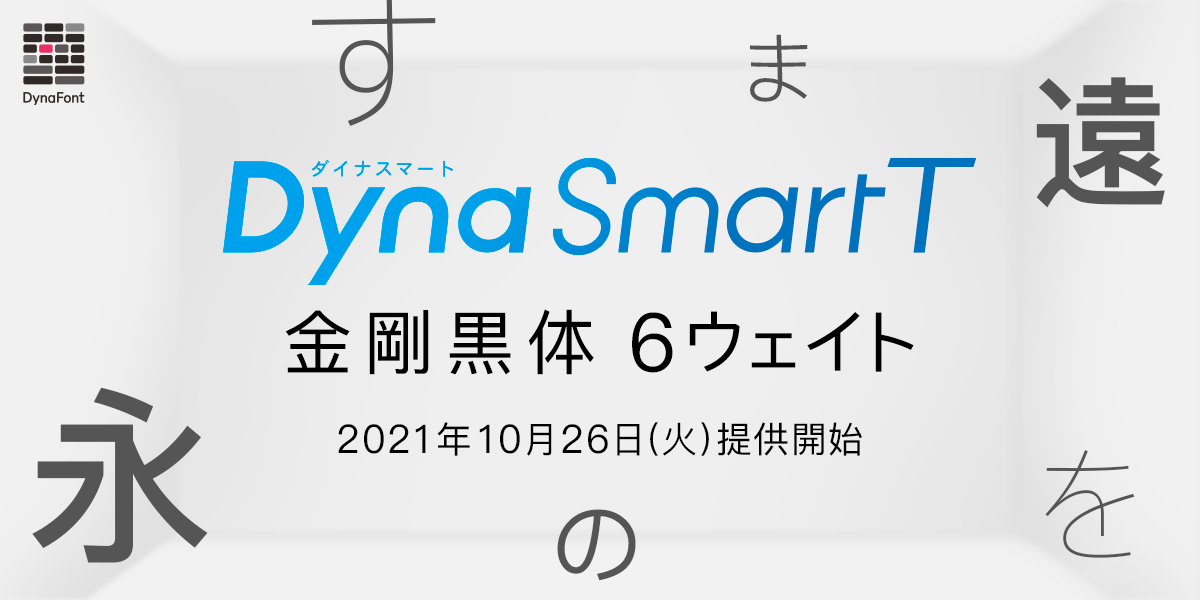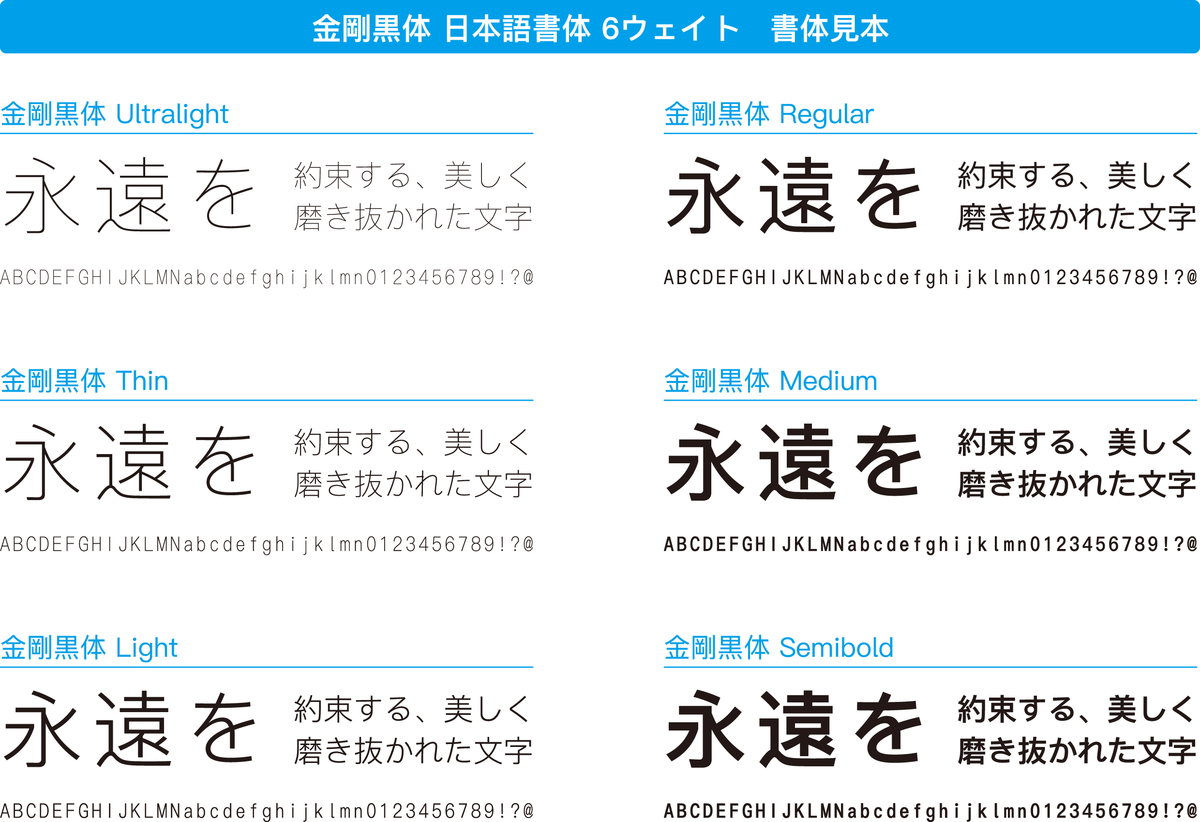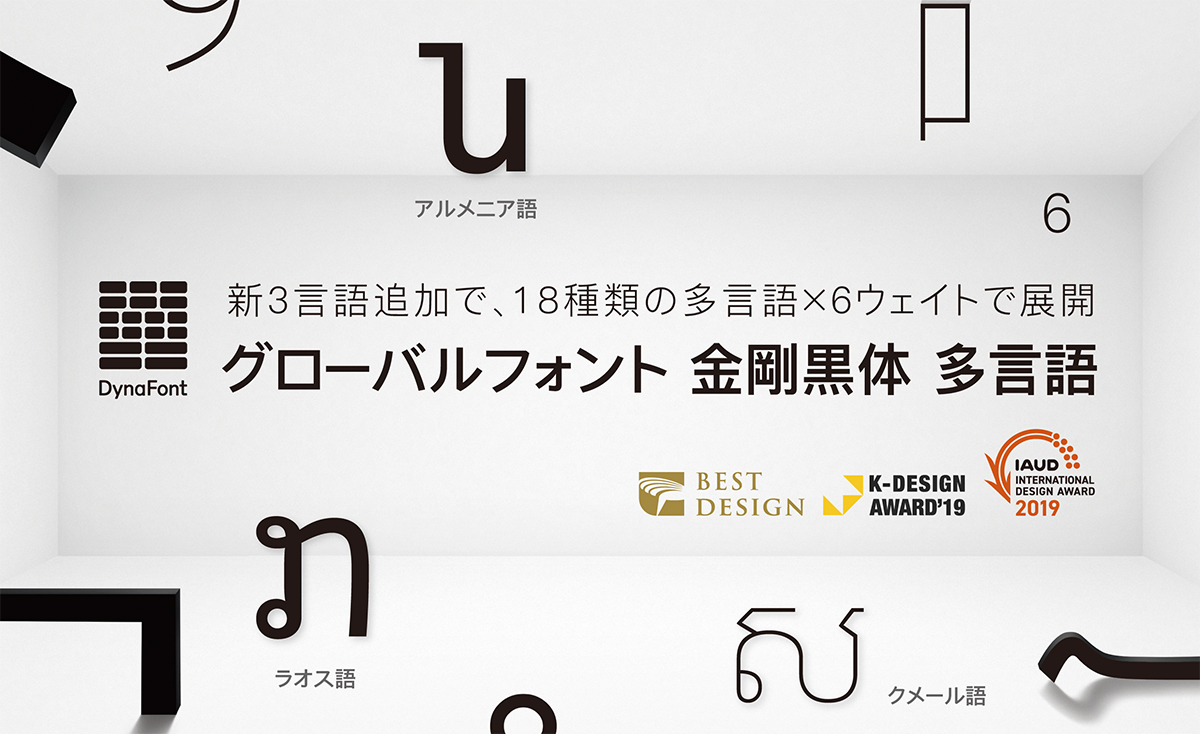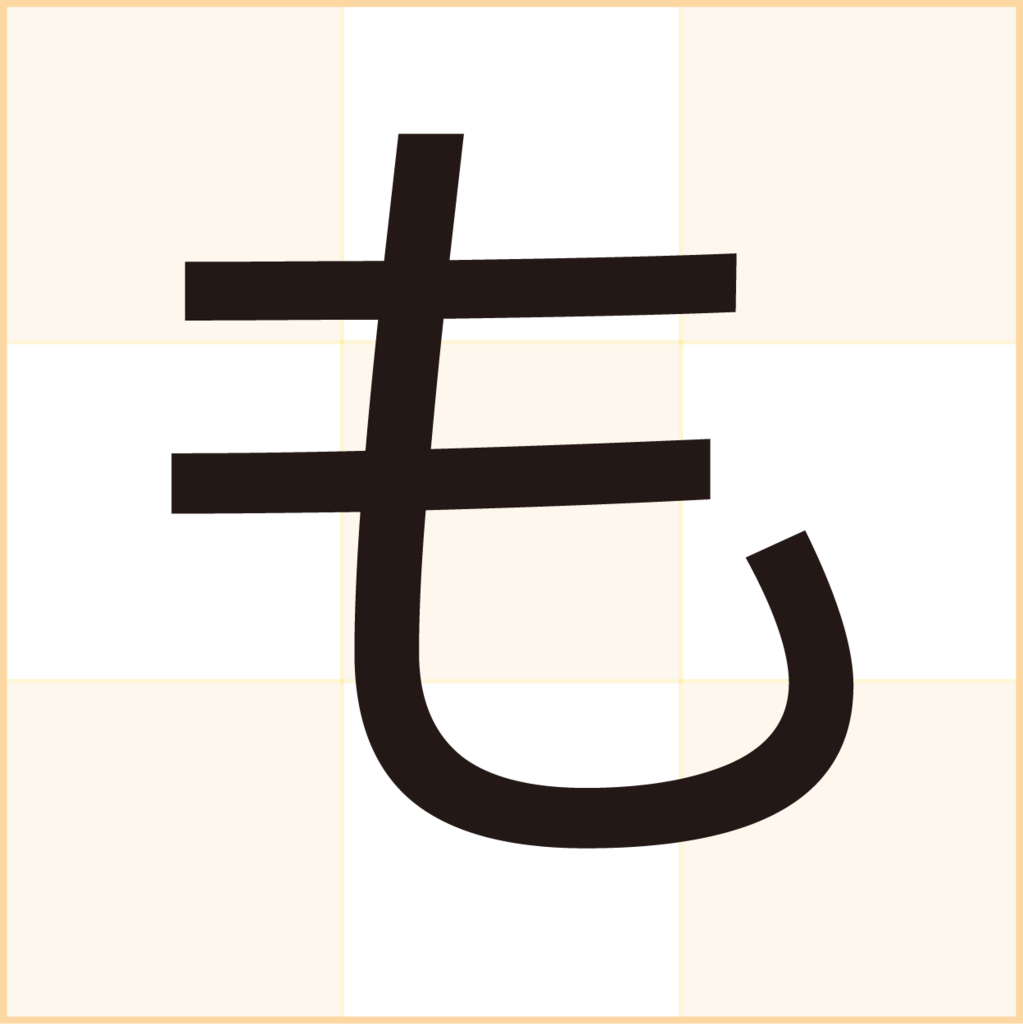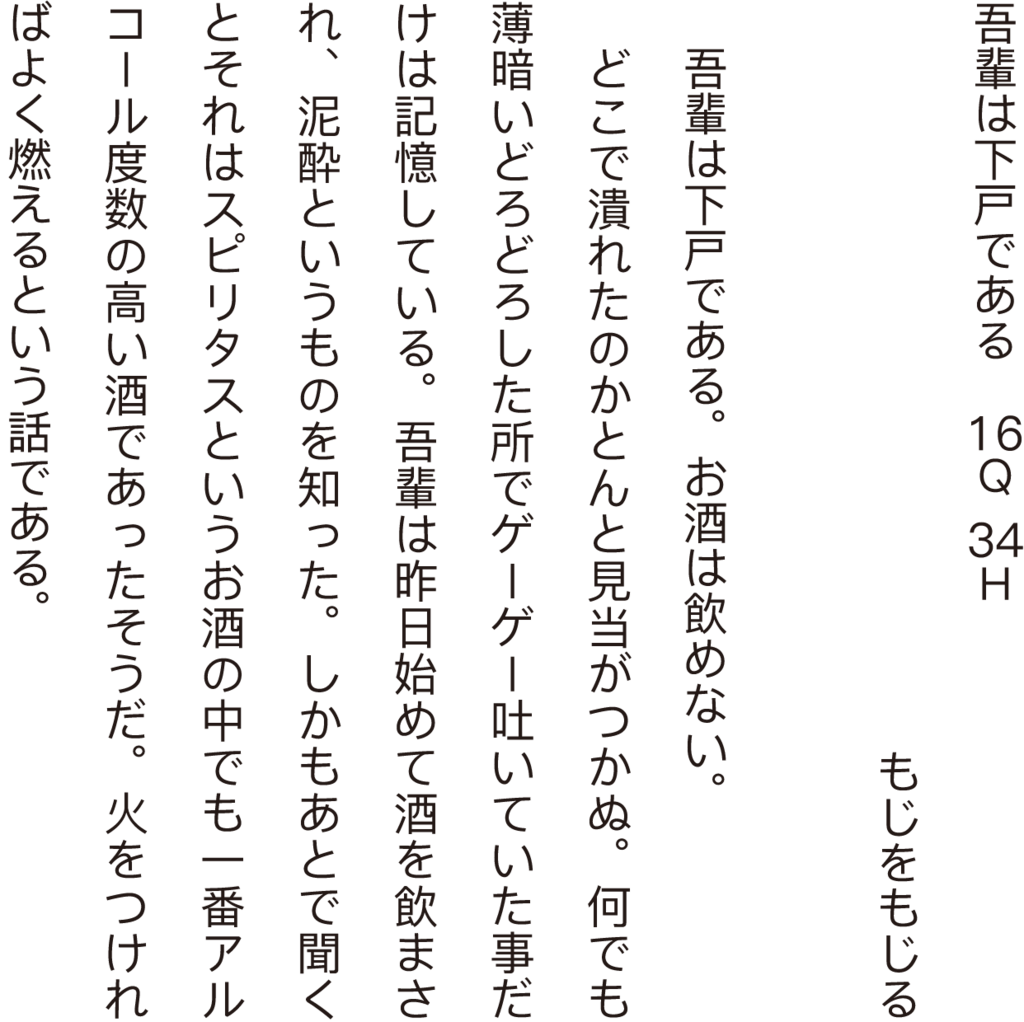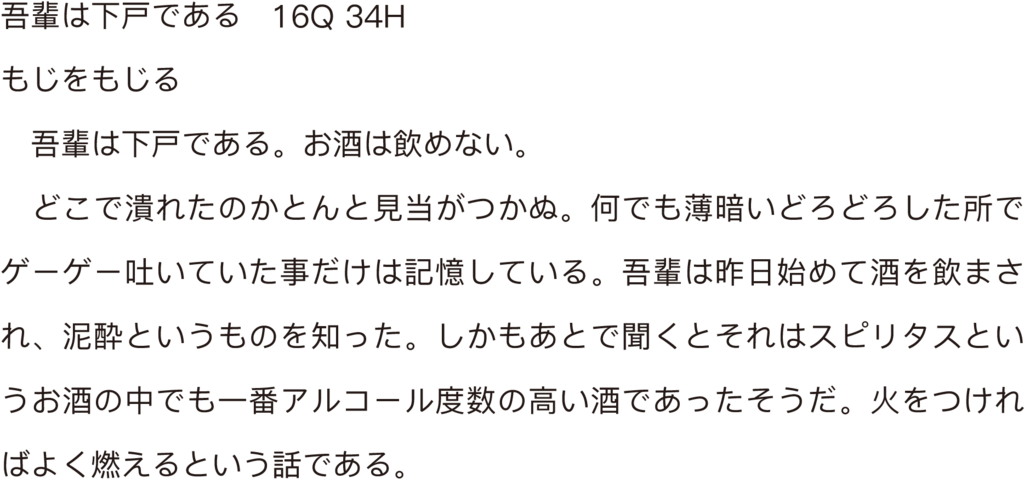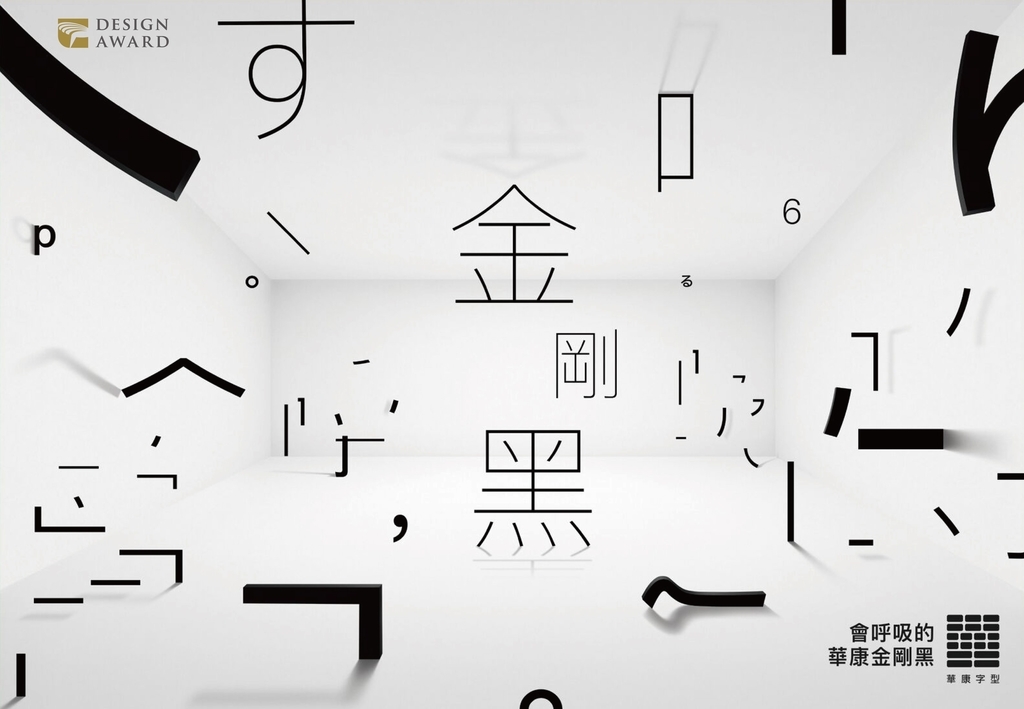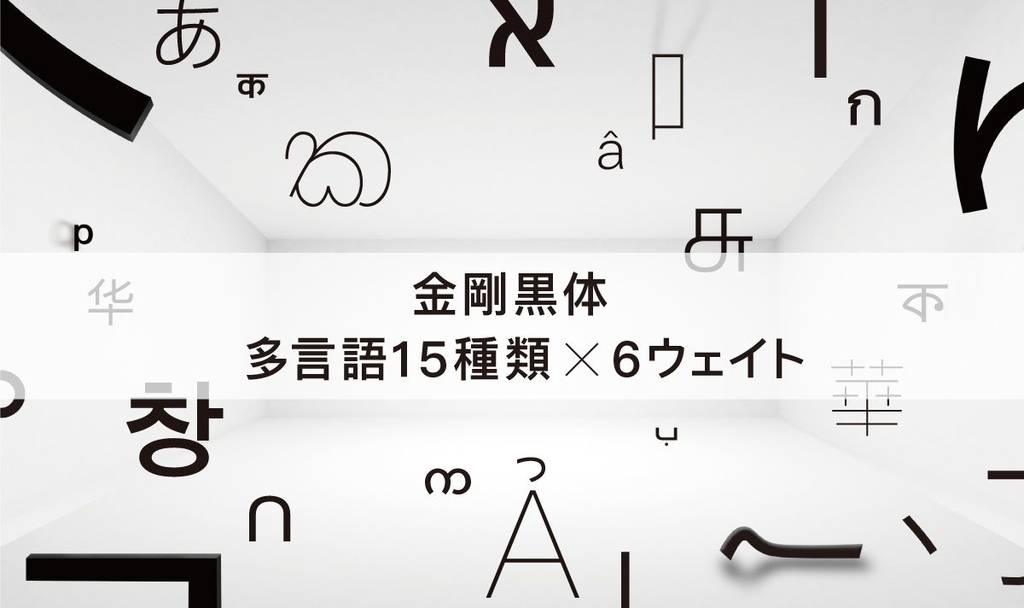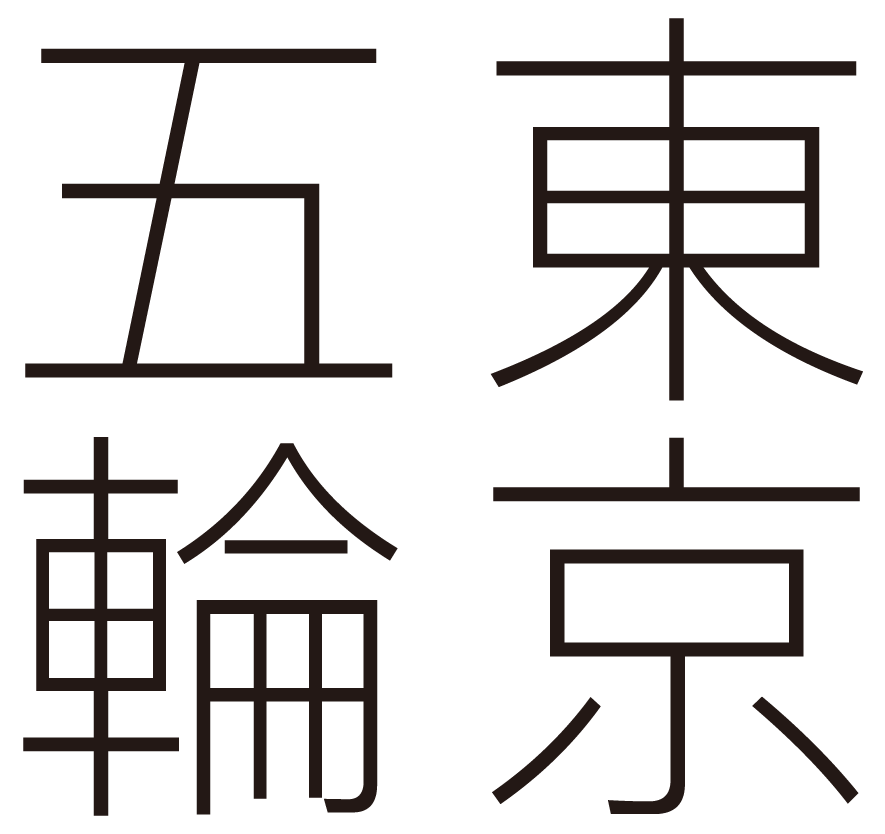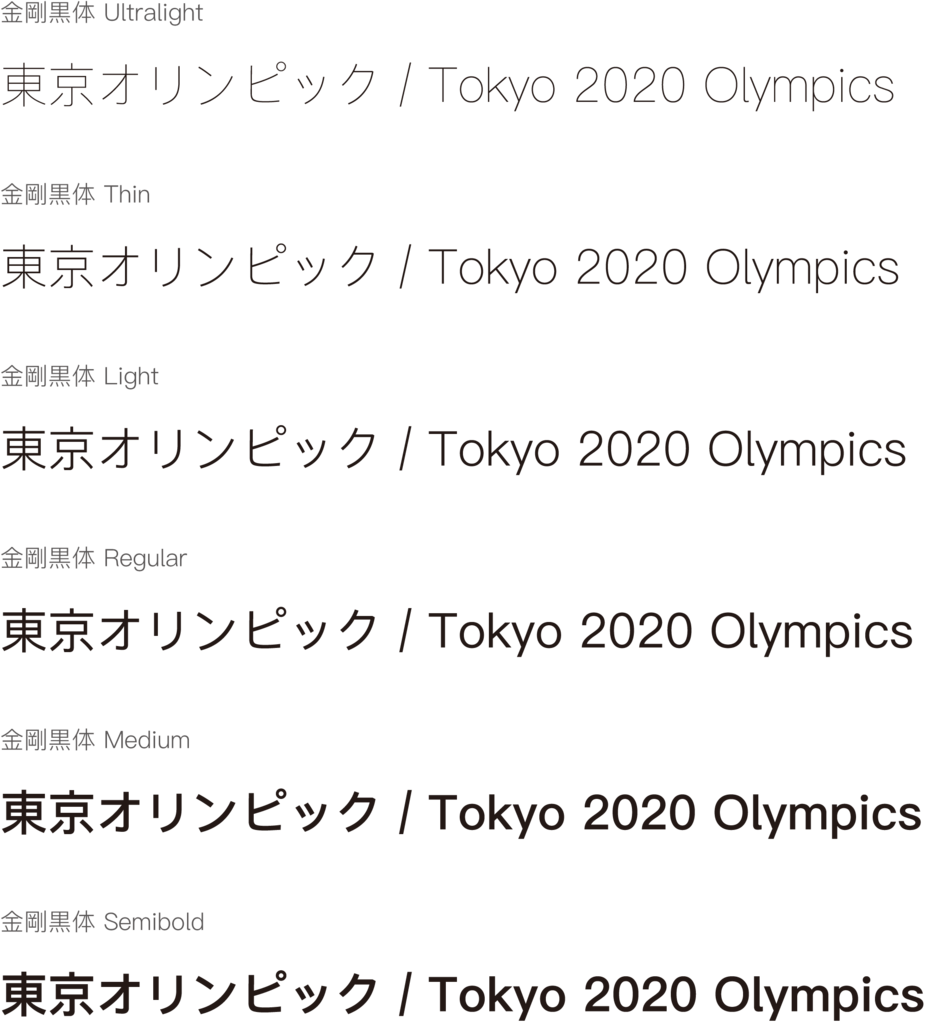
液晶表示に適した18種類の言語を統一されたデザインで使える多言語グロ―バルフォント「金剛黒体」
2017年5月10日、ダイナコムウェア株式会社は、デジタル液晶画面向けに開発されたグローバルフォント「金剛黒体」を発表した。
2018年にダイナフォント年間ライセンス「DynaSmart」シリーズに収録された。ダイナフォント年間ライセンス「DynaSmart V」では金剛黒体の多言語も使用できる他、組込みフォントとしてもリリースされている。
2021年10月26日からDynaSmart Tに「金剛黒体 日本語書体」6ウェイトが追加
DynaSmart Tに金剛黒体追加
2021年10月26日からダイナフォント年間ライセンス「DynaSmart T」に「金剛黒体 日本語書体」6ウェイトが追加された。
「金剛黒体」は、ダイヤモンドの王様と呼ばれるカーボネードのように光輝いた新しいスタイルのUltralight、Thin、Light、Regular、Medium、Semiboldの6ウェイトで展開するゴシック体ファミリー。
シンプルで洗練されたストロークに加え、従来の書体より懐を広げたことで生まれたはっきりとした構造は、視認性を向上させ、また、文字全体に明るく澄みきったような空気感により、あらゆる文書において快適な読み心地をもたらす。
本文での使用から、見出しやキャプションなどに6ウェイトを柔軟に使い分けることで、洗練された文字による統一感のあるレイアウトを作成することができる。
多言語フォント/グローバルフォント「金剛黒体クメール語」、「金剛黒体アルメニア語」、「金剛黒体ラオス語」が2020年6月に「DynaSmart V」に追加
多言語フォント「金剛黒体クメール語」、「金剛黒体アルメニア語」、「金剛黒体ラオス語」が2020年6月5日に「DynaSmart V」に追加された。
多言語フォント「金剛黒体クメール語」、「金剛黒体アルメニア語」、「金剛黒体ラオス語」は多言語フォント「金剛黒体」の新3言語。
これまでに発表している15種類の「金剛黒体 多言語」同様に、各言語の個性にあわせた書き方と書体として統一したデザインを採用。
それぞれUltralight、Thin、Light、Regular、Medium、Semiboldの6ウエイトでファミリー展開。
金剛黒体クメール語
クメール語はインドのブラーフミー系文字に由来しているとされ、カンボジアの公用語として使用されている。母音、子音、二重子音、独立母音といった要素で構成され、上下左右に組み合わせることができるという独特な特徴がある。
金剛黒体クメール語は、正確な書き方を保ちながらも独自の技術により、字母が異なる組み合わせになっても大きさや位置を柔軟に調整することができる。デザイン面では理性と感性のバランスを取り、細かい部分ではクメール文字の柔らかな曲線と幾何学的で左右対称の美しさがそのまま残されており、一部の文字でシンプルなデザインを採用し、すっきりと落ち着いた個性を引き出している。
金剛黒体アルメニア語
アルメニア文字は、ラテン語と同様に左から右に向かって書き進める表音文字で、字母は38文字あり、非常に古い表記システムで書かれる文字。現在、アルメニア語に似たような言語はなく、一般的にインド・ヨーロッパ語族の独立した一語派を形成。
金剛黒体アルメニア語は、ふところがしっかりと取られており、シンプルで爽やかなデザインが小さな文字を表示する場合でも優れた視認性を発揮。デザイン面では、ラテン語と一貫性を持たせながら、アルメニア文字の折れや曲げに見られる独特の書き方を残している。また、字間を調整し、余白部分を削ることで文字を組んだ時の視覚的なバランスを大幅に向上させている。
金剛黒体ラオス語
ラオス語は、ラオスの公用語やその他少数民族が使用している言語。タイ語に近く、美しいループと曲線が特徴的で、独特の風格が漂っている。
金剛黒体ラオス語は、金剛黒体シリーズの特長である字幅が広く、落ち着いたスタイルを継承。また、ラオス語を書く際の運筆を取り入れ、母語話者に指導と校正を依頼することでラオス語らしい滑らかで優雅な美しさを余すところなく表現した書体。
新元号「令和」の合字に金剛黒体6ウェイトが対応
ダイナフォント「金剛黒体」6ウェイトは、明治、大正、昭和、平成といった元号を構成する2文字を全角1文字に入るように圧縮して設計した「合字」に関して新元号である「令和」も対応したことを2019年4月3日に発表した。
グローバルデザインフォント「金剛黒体」の組見本(ウェイトはレギュラー)
多言語でデザインを統一したグローバルデザインフォント「金剛黒体」
ダイナフォント「金剛黒体」は、シンプルで洗練されたストロークに従来の書体より懐を広げたことで、どの液晶画面に搭載しても、今までにない快適な読み心地を実現することができる、いわばグローバルデザインフォント。
金剛黒体は、6種のウェイトと12ヶ国語で展開しておりIoT産業における開発需要に応えることができるグローバルフォントとしてスマートデバイスでの情報伝達をより快適化する。
日本語書体名: DF金剛黒体(こんごうこくたい)/ 英語書体名: DF King Gothic
Ultralight / Thin / Light / Regular / Medium / Semibold
・日本語: JIS X 0208および JIS X 2004標準に準拠
・韓国語: KS X 1001とKS X 1002標準に準拠
・繁体字:Big5-2003標準に準拠
・繁体字(香港):最新のHKSCS-2016標準に準拠
・簡体字:GB18030標準に準拠し、標準局の検査に合格
・豊富な欧文字体を提供し、ISO MES-2のサブセットおよびその他、インド文字、ベンガル文字、アラビア文字、ヘブライ文字、タイ文字、ベトナム文字、ビルマ文字を含む中央アジア、東アジアの言語をサポート。
・ウェイトのカスタマイズ
金剛黒体はVariable Fontによく似たフォント生産テクノロジーを採用し、現在の6種類のウェイトの範囲内で、お客様の要望に沿ってウェイトの微調整を行うことができ、スピーディーに対応することが可能。
・必要なサブセットを結合
金剛黒体は異なるサブセット内に同じフォントがあり、全く同じグリフを共有。そのため、多言語が必要な場合は、カスタマイズして統合することで、フォントファイルを一つにし、効果的にフォント容量を縮小可能。
・金剛黒体の漢字は、各地域の書き方に合わせてデザイン。
・記号は言語の違いに基づいて、位置を調整。